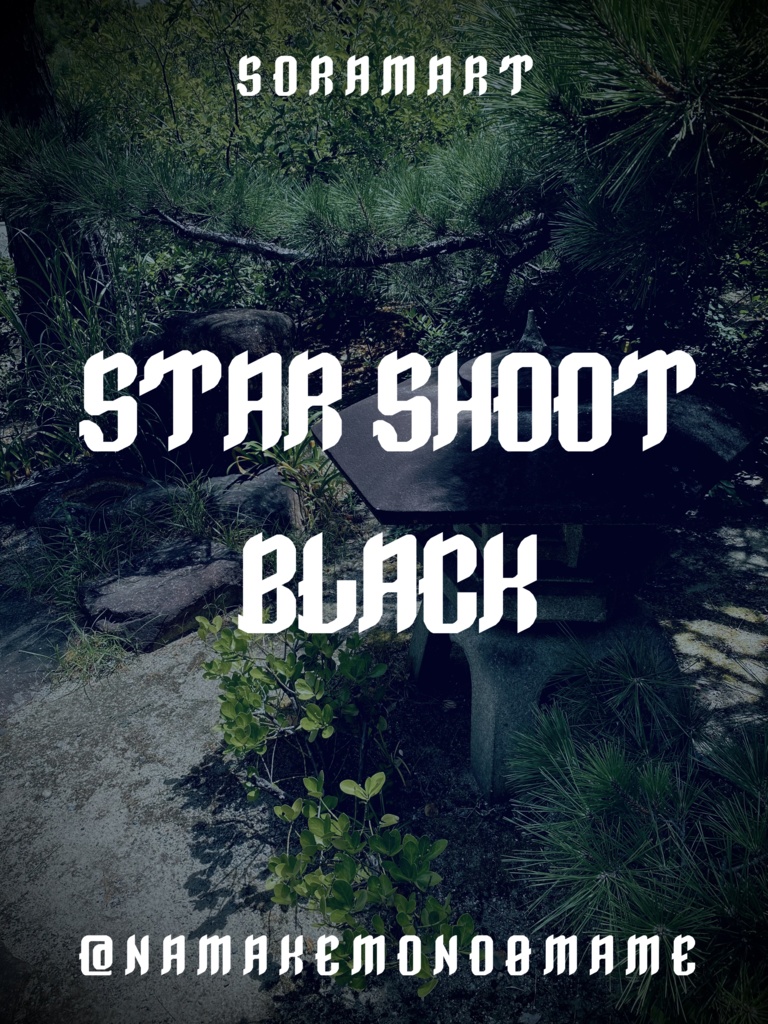
そらマートフォントデータ”Star Shoot Black”Digital2,500 JPYAdd to CartBuy a GiftAbout Gift流れるようなラインのレトロ調ブラックレター・フォント "Star Shoot Black" です。 「TrueTypeフォントファイル」という形式です。 ダウンロードした後、Zipファイル内のデータをインストールしてお使いください。 このフォントは商用利用可となっております。 お客様の制作・創作活動のお役に立てれば幸いです。 ※使用上の注意事項などは、添付のReadmeをお読みください。そらマートVisit FANBOX!Fontsフォントデータ”Solid Voltage Strike”そらマート200 JPYFontsフォントデータ”Solid Voltage”そらマート0 JPYFontsフォントデータ”Henge Edge Rock”そらマート2,500 JPYFontsフォントデータ”Henge Edge Tall”そらマート0 JPYFontsフォントデータ”Henge Edge”そらマート0 JPYFontsフォントデータ”Chisel Stroke Wide”そらマート2,500 JPYFontsフォントデータ”Chisel Stroke”そらマート2,500 JPYFontsフォントデータ”Crushed Can Serif Empty”そらマート2,500 JPYFontsフォントデータ”Crushed Can Serif Wide”そらマート2,500 JPYFontsフォントデータ”Crushed Can Serif”そらマート2,500 JPYFontsフォントデータ”Dolce Cube Tall”そらマート2,500 JPYFontsフォントデータ”Dolce Cube”そらマート2,500 JPYFontsフォントデータ”Eight-bit Quest Wide”そらマート2,500 JPYFontsフォントデータ”Eight-bit Quest”そらマート2,500 JPYFontsフォントデータ”Tonik Crate”そらマート2,500 JPYFontsフォントデータ”Vapor Sprout Edge”そらマート2,500 JPYFontsフォントデータ”Vapor Sprout Wide”そらマート2,500 JPYFontsフォントデータ”Vapor Sprout”そらマート2,500 JPYFontsフォントデータ”Star Shoot Ray”そらマート2,500 JPYFontsフォントデータ”Star Shoot Black Wide”そらマート2,500 JPYSee More